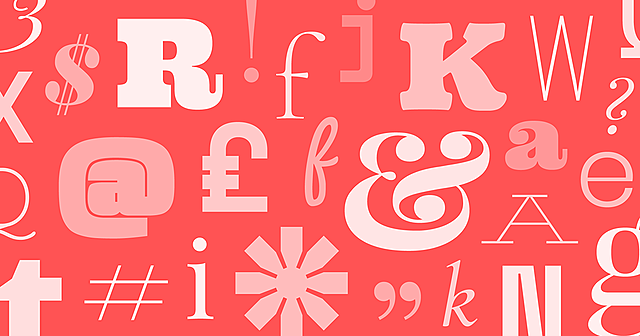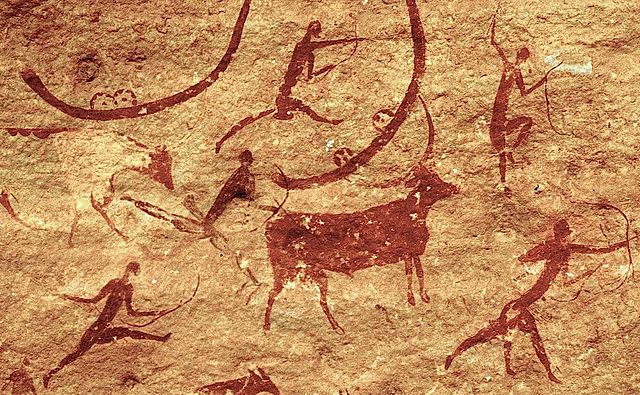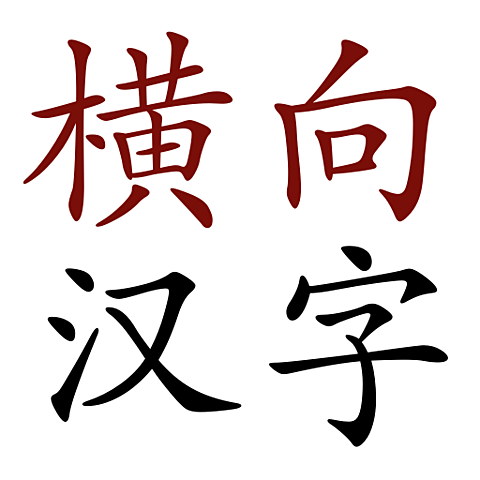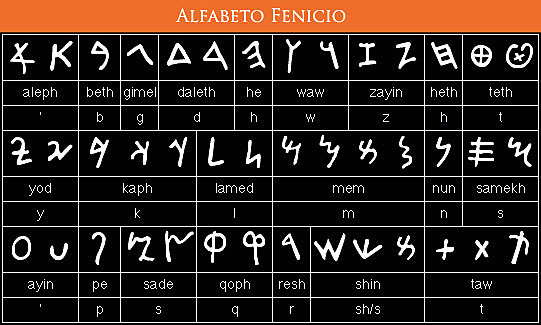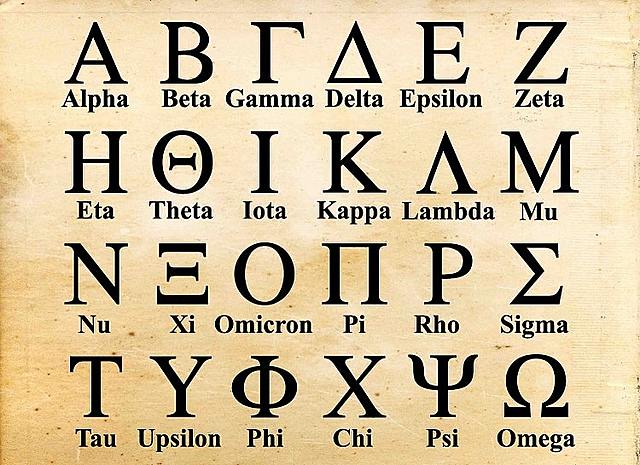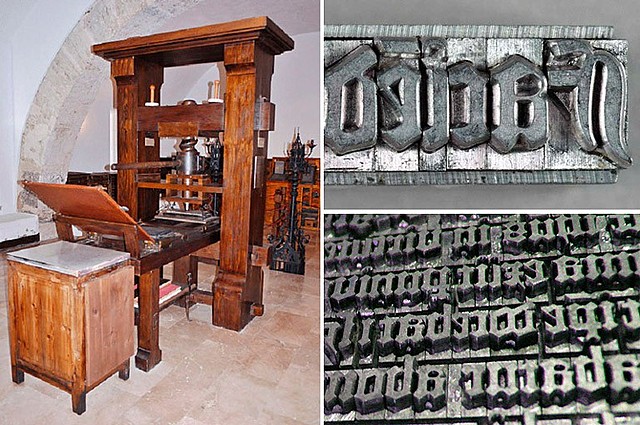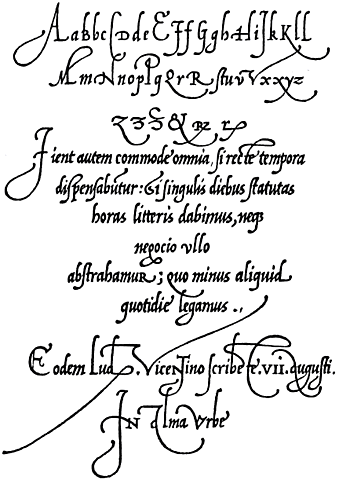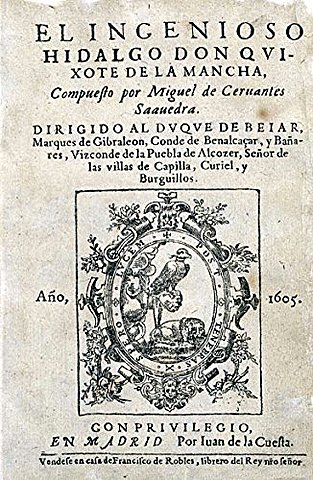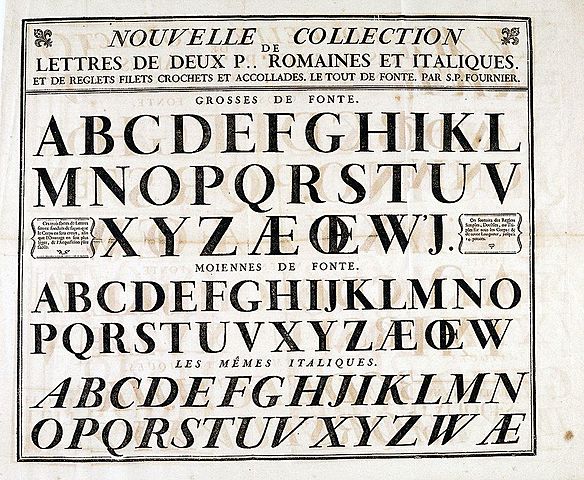
Manifestaciones artísticas que representaban personas y animales.
Escritura sobre tablillas de arcilla húmedas, mediante un tallo vegetal biselado en forma de cuña.
Inventado por los antiguos egipcios basados en pictogramas. Usaron tres tipos de escritura: Jeroglífica, Hierática y Demótica.
En china se desarrolla la caligrafía y usan logo-gramas.
Los fenicios desarrollan el Protoalfabeto que es el primer alfabeto fonético (20 signos mágicos y consonantes)
Los griegos toman el Alfabeto Fenicio y agregan vocales.
Los romanos separan palabras, establecen sistema de puntuación y cambian el sentido de la escritura de izquierda a derecha.
Surge la capital rústica, cursiva romana y la minúscula carolingia
Surge la holografía.
Surge la escritura gótica en Suiza. -
Se desarrolla en Alemania una técnica para elaborar moldes de tipos móviles metálicos para impresión de letras individuales.
Se introduce la imprenta en Francia
Se crea el primer manual de escritura en el siglo XVI. En 1523 se publico el segundo manual impreso con tipos itálicos.
Novedades tipográficas tienen origen en Francia, muestran una creación de ediciones a mano de tipos verdaderamente interesantes.
Se imprimen los libros de bolsillo clásicos de Miguel de Cervantes
Pierre Simon Fournier inicio la estandarización del tamaño de los tipos al publicar su primera tabla de proporciones
Crea la Tipografía: Baskerville
Mejora la prensa y aporta nuevos papeles y tintas. -
Ambrosio Didot establece la unidad de medida "Punto Didot"
invención de la (linotype) maquina usada en la composición tipográfica
Se convierte en el tipo mas leido a mediados del siglo, fue diseñado por Stanley Morrison y Victor Larden para el periódico londinense The Times; esta inspirado en un tipo de Platin del siglo XVIII.
Consiste en una máquina que proyectaba una luz a través de un negativo que posee los caracteres individuales de una fuente determinada. Mediante juegos de lentes, la luz que proyecta el tipo permite ampliarlo y reducirlo de tamaño con respecto al tamaño del negativo. Una vez escrito el texto, la película se procesaba químicamente para después ser usada a conveniencia.
Ofrece soporte para trabajar con objetos vectoriales, con “tipos de contorno” con lineaturas de semitonos profesionales, capacidad de generar puntos de semitonos de distintas formas y capacidad de gestionar hasta 256 tonos de gris distintos en una impresión.
Capacidad, calidad y definición.